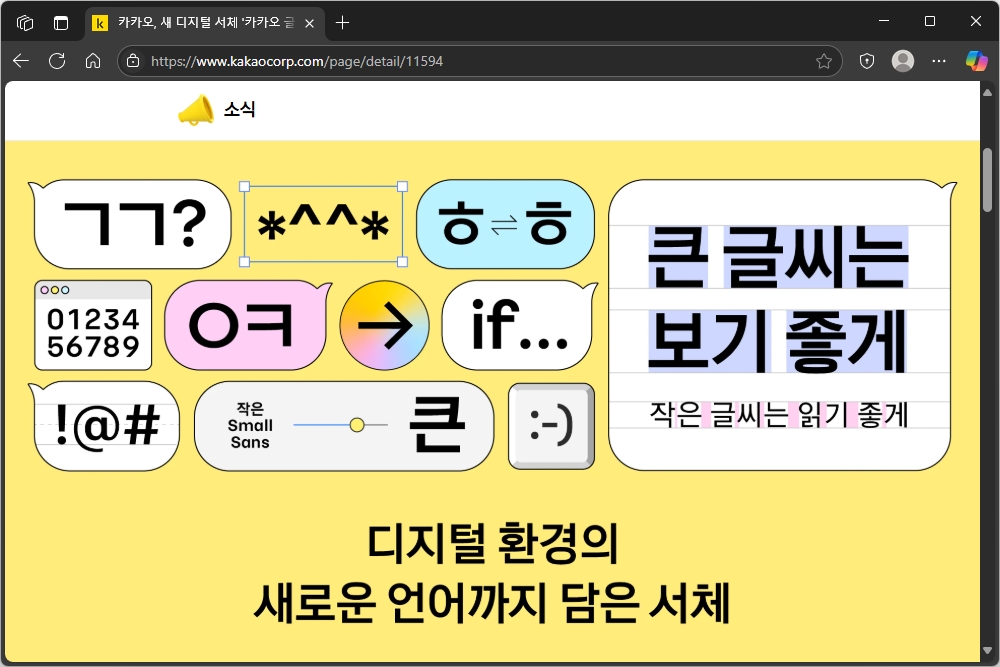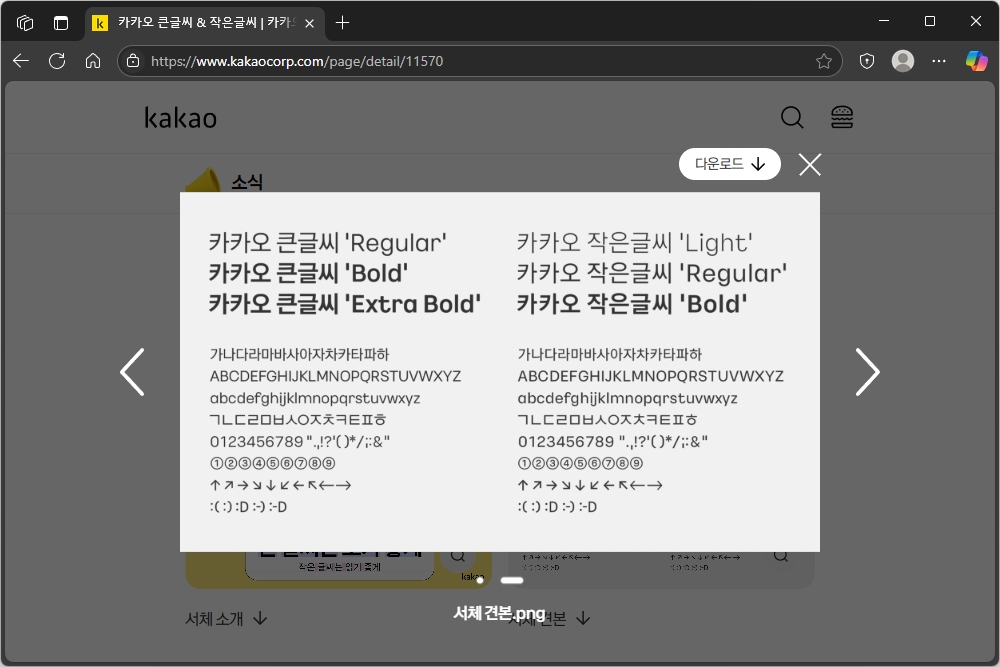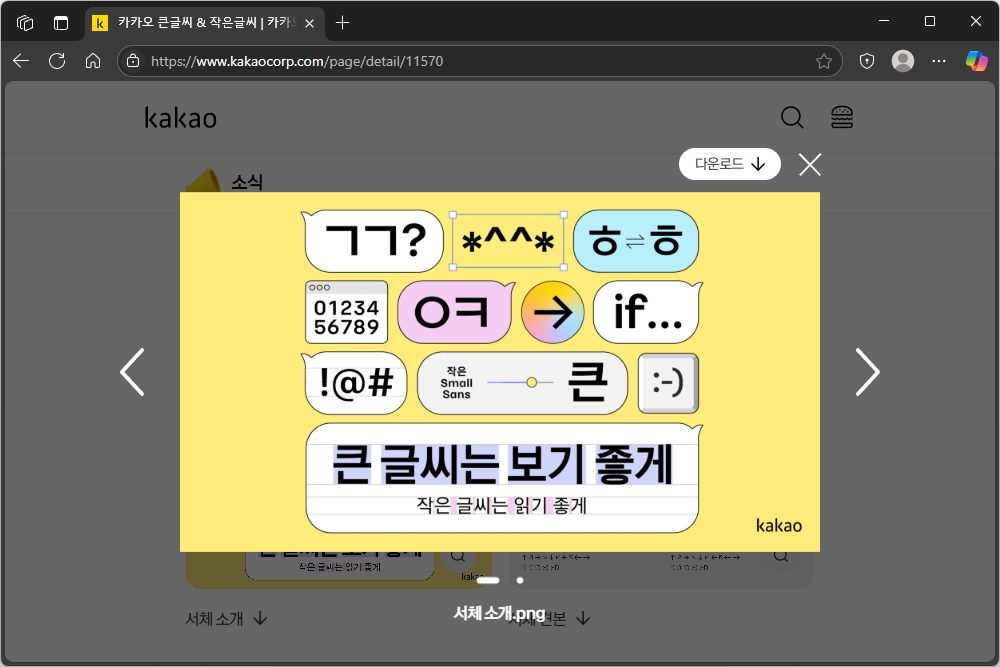
디지털 콘텐츠를 제작하다 보면 가장 많이 신경이 쓰이는 부분 중의 하나는 바로 폰트라고 할 수 있는데요. 분위기에 맞는 폰트를 찾는 것은 생각보다 찾기 어렵습니다. 특히 상업적 폰트를 잘못 사용하면 큰 문제가 될 수 있기 때문에 상당히 주의를 해야 합니다. 그래서 기회가 될 때마다 무료 폰트들을 수집하고 있는데요. 이번에 카카오에서도 새로운 디지털 서채 “카카오 글씨”를 공개했습니다. 그래서 이번 포스팅에서 다운로드와 적용 방법을 확인해 보도록 하겠습니다.
“큰글씨와 작은글씨”
새로운 카카오 폰트의 경우에는 큰글씨와 작은 글씨로 구분되어 있는데요. 큰 글씨는 그래픽적인 요소가 강조된 형태이고 작은 글씨는 작은 크기의 모바일 디바이스에서도 읽기 편하도록 자간에 차이가 있는 것을 확인할 수 있습니다. 큰 회사에서 출시한 폰트이기 때문에 사소한 부분에도 많은 신경을 쓴 것으로 보입니다.
“완성도 높은 폰트”
카카오 폰트를 간단하게 살펴본 경험을 이야기하면 특색이 크게 있어서 포인트로 사용할 수는 없지만 무난하게 완성도 높은 디자인을 채택하고 있어서 다양한 방식으로 활용할 수 있는 서체라고 생각되었습니다. 특히 상업적 사용도 가능하기 때문에 다양한 방식으로 활용해 보시길 바랍니다.